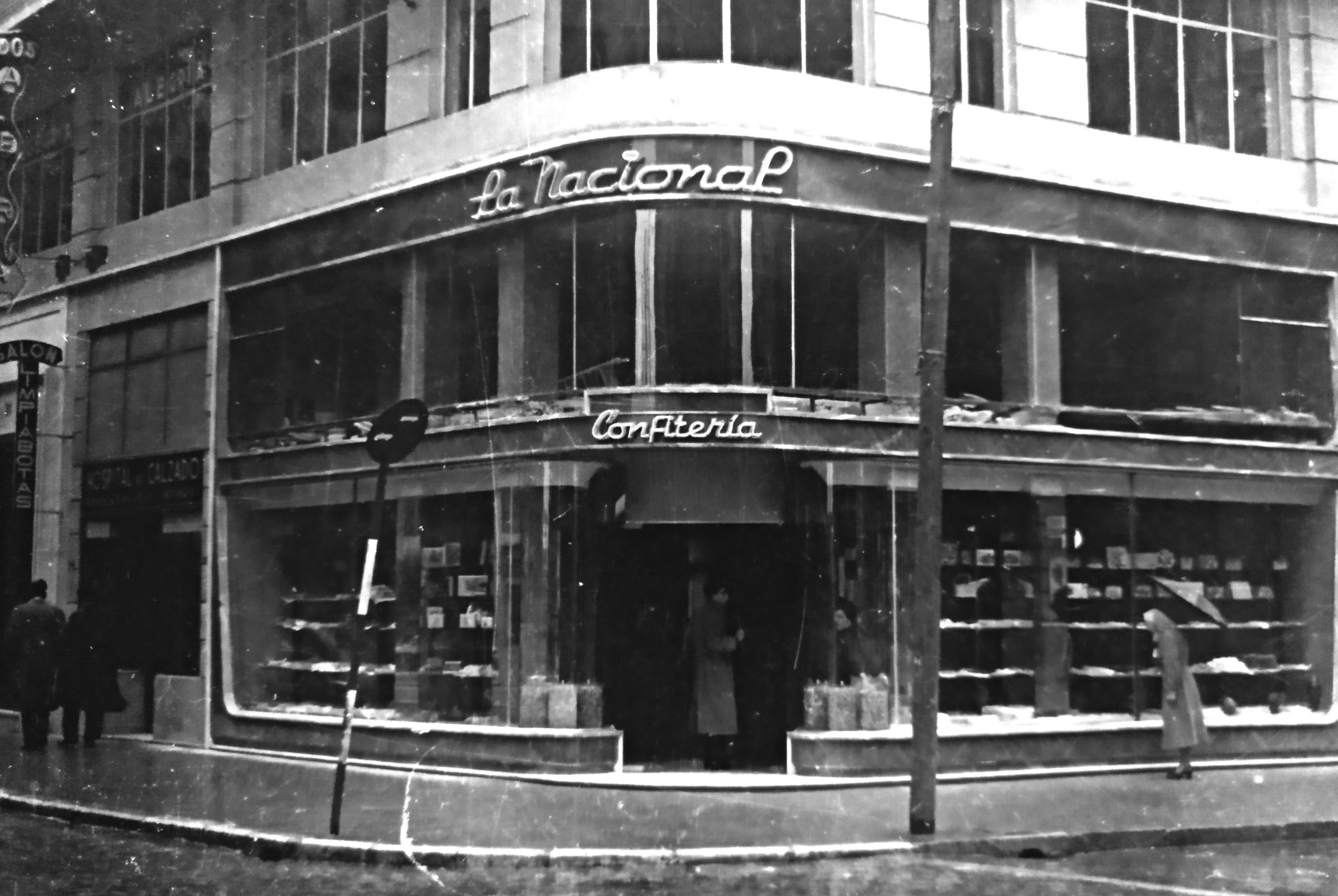
Confitería «La Nacional»
La Nacional estuvo en los años 50 en lo que hoy es una clínica dental y en navidades ha sido una tienda de juguetes, esquina Isabel II con la calle Cádiz. En la fotografía que documenta el rótulo, se puede ver perfectamente el «Hospital del Calzado».
Tenía un escaparate característico con vidrios curvos a la entrada y un rótulo hecho en neón con una tipografía fina característica, que en parte puede recordar a la de Calzados Benito de los años 60. También es curioso el punto de la «i».
Confitería La Nacional, años 50. (Colección César Pombo)